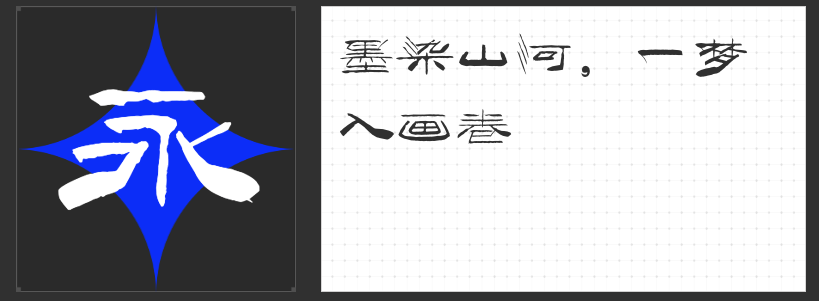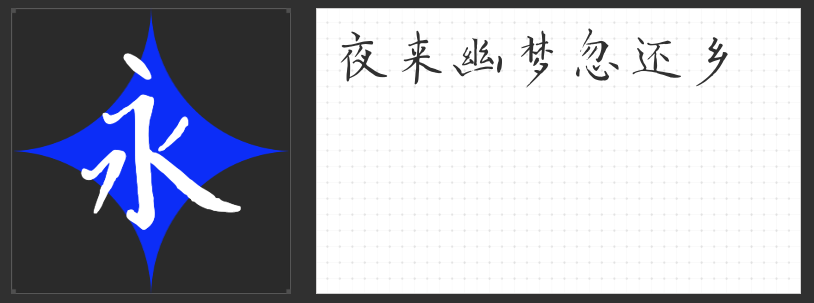
笔墨凝韵:四款书法字体开启设计新境界
在设计的多元宇宙中,书法字体以独特的东方美学气质,成为连接传统与现代的视觉纽带。本文精选四款风格迥异的书法字体,它们以精湛的笔墨语言诠释东方韵律,为设计注入深厚的文化底蕴与艺术张力。
一、云书法玉兰行楷体
以行云流水般的动态美学重塑书写意境。其字形结构匀称而不失灵动,主笔画舒展如舞者飞扬的衣袂,通过块面对比强化视觉层次。运笔时提按顿挫间暗藏韵律,牵丝连带自然天成,既保留毛笔书写的原生质感,又赋予现代设计所需的节奏感。无论是影视海报的视觉冲击,还是文创产品的雅致格调,皆能以灵动笔触传递东方气韵。
二、云书法永刚漆书体
以漆器般的厚重质感重构书写形态。笔画如刀刻斧凿般刚劲有力,撇捺转折处透露出从容气度,框架结构端庄如青铜鼎彝。这种将传统笔墨与现代构成主义融合的创意,使其在包装设计中既能承载品牌厚重感,又能在广告平面中形成独特的视觉符号,实现传统艺术与商业传播的完美平衡。
三、云书法朴拙小楷
以文人书法的雅致格调重构现代审美。融合二王笔法的圆润遒劲与欧体结构的严谨舒展,在方寸之间构建出动静相宜的视觉平衡。其古雅气质既能为影视宣传增添文化厚度,又能在包装设计中营造高级感,是连接古典美学与当代设计的理想载体。
四、云书法铁笔隶书体
以金石篆刻的力度重塑隶书风骨。宽扁字形中暗藏几何美学,横竖对比强化视觉张力,笔画转折处的粗细变化如乐章起伏。这种将篆刻刀法转化为书写语言的创新,使其在需要庄重感的场景中(如文化类海报、传统品牌包装)展现出独特的艺术价值。
这四款字体以不同的笔墨语言诠释东方美学,为设计师提供了跨越时空的创作工具。它们既是传统书法精神的当代转译,更是设计语言系统中的重要维度,在商业传播与艺术表达之间架起一座充满诗意的桥梁。